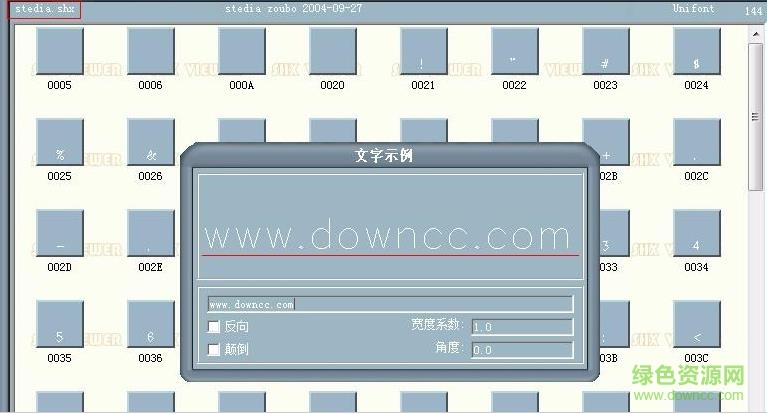
cad stedia.shx
stedia.shx字體經(jīng)常運(yùn)用在眾多生產(chǎn)設(shè)計(jì)以及工業(yè)圖紙?jiān)O(shè)計(jì)過(guò)程中,通過(guò)在二位cad軟件中進(jìn)行文字插入以及眾多藝術(shù)字體的顯示效果讓你能夠獲得更加優(yōu)質(zhì)的圖紙制作,快來(lái)綠色資源網(wǎng)下載吧!
stedia字體小編點(diǎn)評(píng)
stedia.shx在眾多cad字體中首屈一指,能夠帶給你最佳的英語(yǔ)字體顯示效果,讓你的英文在設(shè)計(jì)過(guò)程中十分的方正規(guī)整!
stedia字體
stedia.shx字體介紹